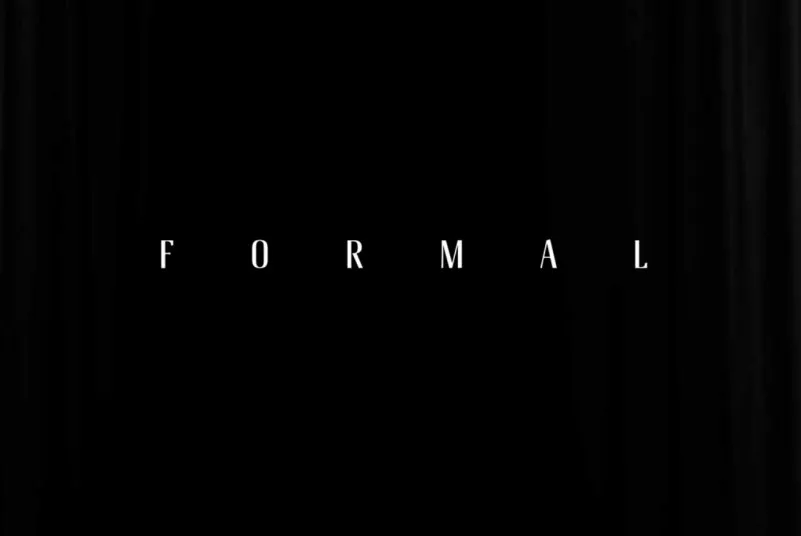
Formal Inline Typeface – Download Grátis
Formal Inline Typeface é uma fonte que transmite força e originalidade com suas formas extremas e peso super pesado, tornando-a irresistível em qualquer meio. Ideal para anúncios ou design web onde você deseja destacar mensagens importantes e emocionantes. Suas linhas levemente curvadas dão vida a uma aparência moderna e elegante, garantindo que seu texto seja notado em qualquer projeto de embalagem, cartaz ou site. Formal Inline Typography é perfeita para celebrar os sentimentos mais profundos da alma através do design gráfico, oferecendo um toque único e especial ao mesmo tempo. É uma opção ideal tanto para o público empresarial quanto para designers criativos que desejam expressar seu ponto de vista com autenticidade e impacto visual forte em seus trabalhos.